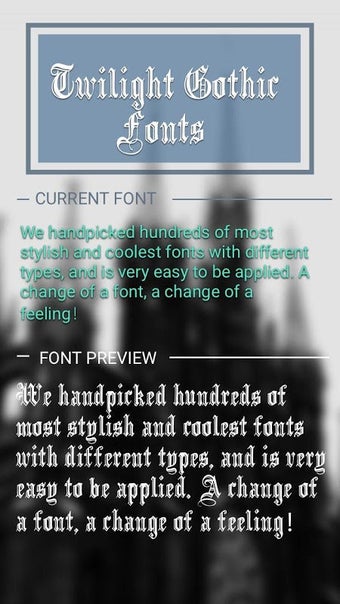
Einzigartige Schriftarten für Android-Nutzer
Twilight Gothic Font for FlipFont ist eine kostenlose Android-App, die Benutzeroberflächen durch stilvolle Schriftarten personalisiert. Diese App bietet eine Vielzahl von Gothic-Schriftarten, die sich leicht in die Benutzeroberfläche integrieren lassen. Die Installation ist einfach und erfordert lediglich die Aktivierung der Schriftart über die Einstellungen des Geräts. Die App ist mit Android 13.0 und höher kompatibel und bietet eine benutzerfreundliche Oberfläche, die es einfach macht, die gewünschten Schriftarten auszuwählen und anzuwenden.
Die App bietet nicht nur ästhetische Anpassungen, sondern ermöglicht auch eine individuelle Gestaltung von Textnachrichten und sozialen Medien. Die Schriftarten sind gut lesbar und eignen sich sowohl für den alltäglichen Gebrauch als auch für kreative Projekte. Im Vergleich zu ähnlichen Apps bietet Twilight Gothic eine einzigartige Auswahl an Gothic-Schriften, die sich von anderen Standard-Schriftarten abheben. Die App ist kostenlos, was sie zu einer attraktiven Option für alle macht, die ihr Android-Gerät personalisieren möchten.